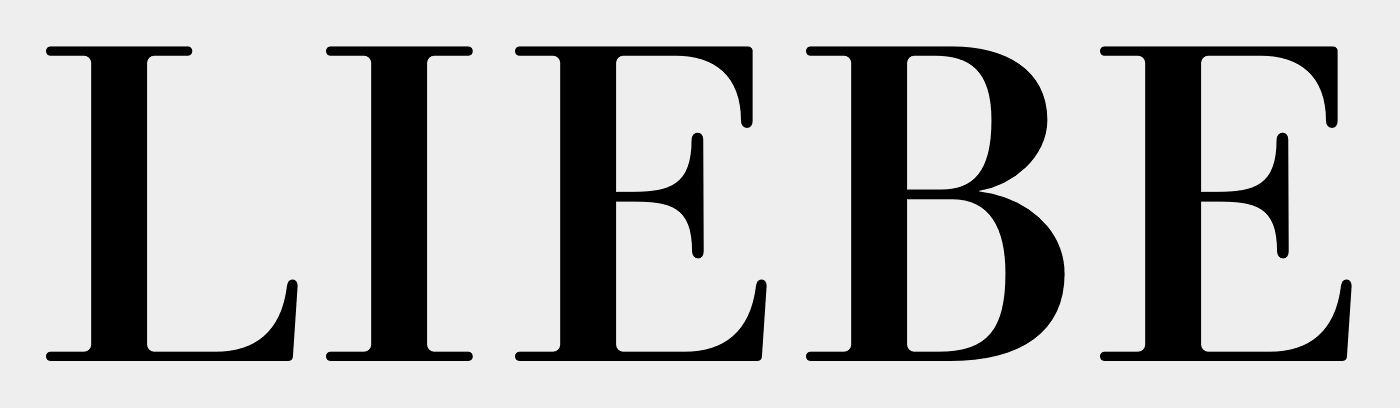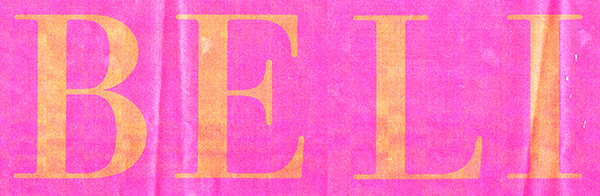
Also wir alle suchen nach Liebe.
Ich suche aber eigentlich eine Schrift, die mir nur in dem einen Wort LIEBE vorliegt. Mit vier Buchstaben komme ich bei den üblichen Suchhilfsmitteln nicht weiter. Daher hier meine Frage. Was ist das für eine Schrift? Markant scheinen mir die abgerundete Serifenenden. Interessant finde ich auch, dass beim "E" die untere Seriefe, (wie auch beim "L") leicht geneigt, die obere aber senkrecht steht. Bei Menschen nennt man sowas Unterbiss ;-)
Tatsächlich brauche ich nur dieses eine Wort für die Wandgestaltung eines Yoga-Raumes.: LIEBE, nicht BELI
Ich muss sie übersehen haben, denn ich bin die Listen der Egyptienne bei den großen Anbietern durchgegangen.
Mal sehen, vielleicht finde ich noch andere Verwendungszwecke. Die abgerundeten Serifenenden finde ich gerade bei sehr großen Schriftgraden interessant. Und schöne Ligaturen gibbet auch.
Tja, das liegt eben daran, dass dies hier keine Egytienne ist, ganz und gar nicht.
Maßgebliches Erscheinungsbild einer Egyptienne ist ja:
1, gleichbleibende (oder zumindest optisch gleich erscheinende) Strichstärken - auch der Serifen, die zumindest annähernd so breit wie die Sticstärke im Buchstaben selbst sind.
2. rechteckige Serifen.
Tja, das liegt eben daran, dass dies hier keine Egytienne ist, ganz und gar nicht.
Das hast du natürlich recht.
Übrigens: die Vorlage hatte deutlich stärkere Grundstriche. Weil das aber der einzige Unterscheid war, ließ sich das bei vier Buchstaben leicht anpassen.